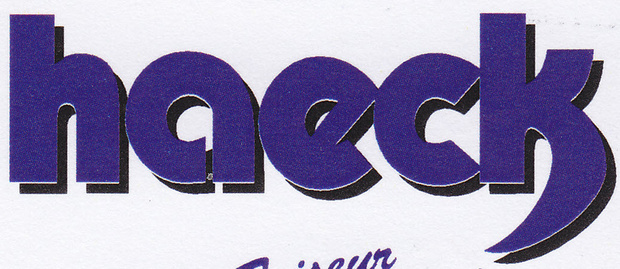
Ich suche eine Schrift. Wer kann helfen?
ich soll für einen Kunden die Visitenkarte neugestalten.
Leider gibt es keine Infos mehr über die verwendete Schrift und auch keine Dateien die ich verwenden kann.
Wer kennt die folgende Schrift?
Ich bin jetzt bei weitem kein so ein Schriften-Crack wie manche anderen Mitglieder hier, aber die Schrift geht mir sehr in Richtung "Bauhaus".
Das "k" ist aber definitiv handgeschustert.
Jetzt muss ich nur noch irgendwie das "k" bearbeiten.
Die ist aber noch mal künstlich aufgefettet worden, oder? Vergleiche mal das "e" aus dem Beispiel
Im Beispiel hat der untere Teil ja gar keine Definition mehr, das "e" sieht mehr aus wie Pac-Man mit neuen Augen ;)
Mir ging es jetzt nicht darum ob das die semibold ist oder nicht, sondern nur um den Schriftnamen an sich. Und aufgefettet ist sie nicht, das sieht nur durch den schwarzen Schatten dahinter so aus. Zoom mal rein, dann siehst du dass das lila e genau deinem Beispiel entspricht :-)